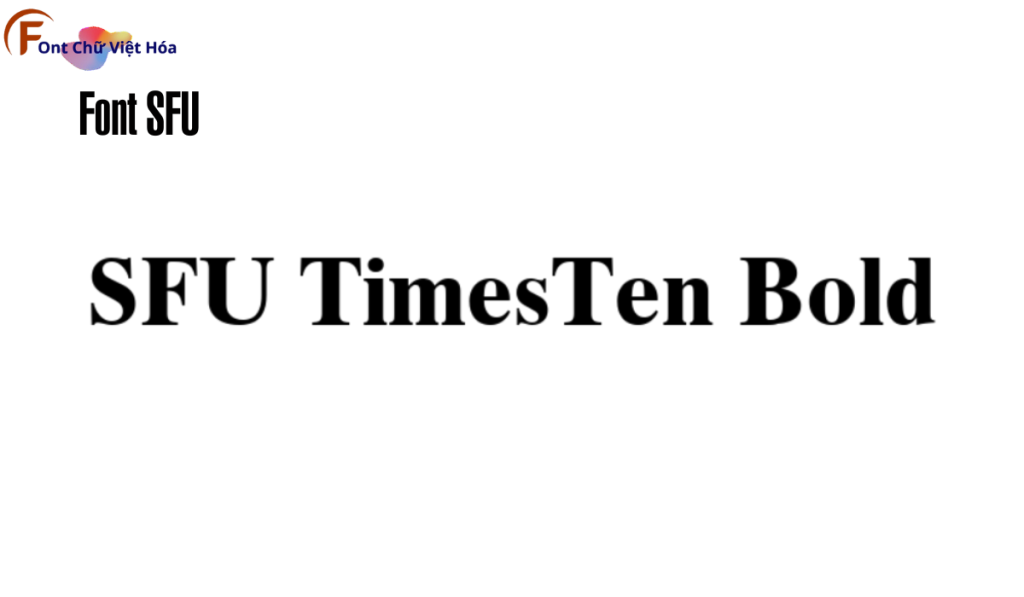
Font SFU Times Ten Bold Việt Hóa
Tác giả: SFU Times Ten
Bộ Font: SFU
Phân loại: Cổ điển
Kiểu chữ: Serif
Độ dày: Bold
Font SFU Times Ten Bold Việt Hóa là một font chữ độc đáo, mang phong cách serif cổ điển với các đường nét thanh thoát và tinh tế, thuộc bộ font SFU. Thiết kế của SFU Times Ten Bold tập trung vào sự sang trọng và dễ đọc, đặc biệt phù hợp cho các thiết kế đòi hỏi tính thẩm mỹ cao như sách, báo, và tài liệu. Với tỷ lệ chữ cân đối và các đường nét rõ ràng, font này tạo ra ấn tượng thị giác mạnh mẽ và giúp tối ưu hóa không gian trong thiết kế. Font này cũng đã được Việt hóa, mang đến sự linh hoạt và tiện dụng cho các dự án thiết kế bằng tiếng Việt.